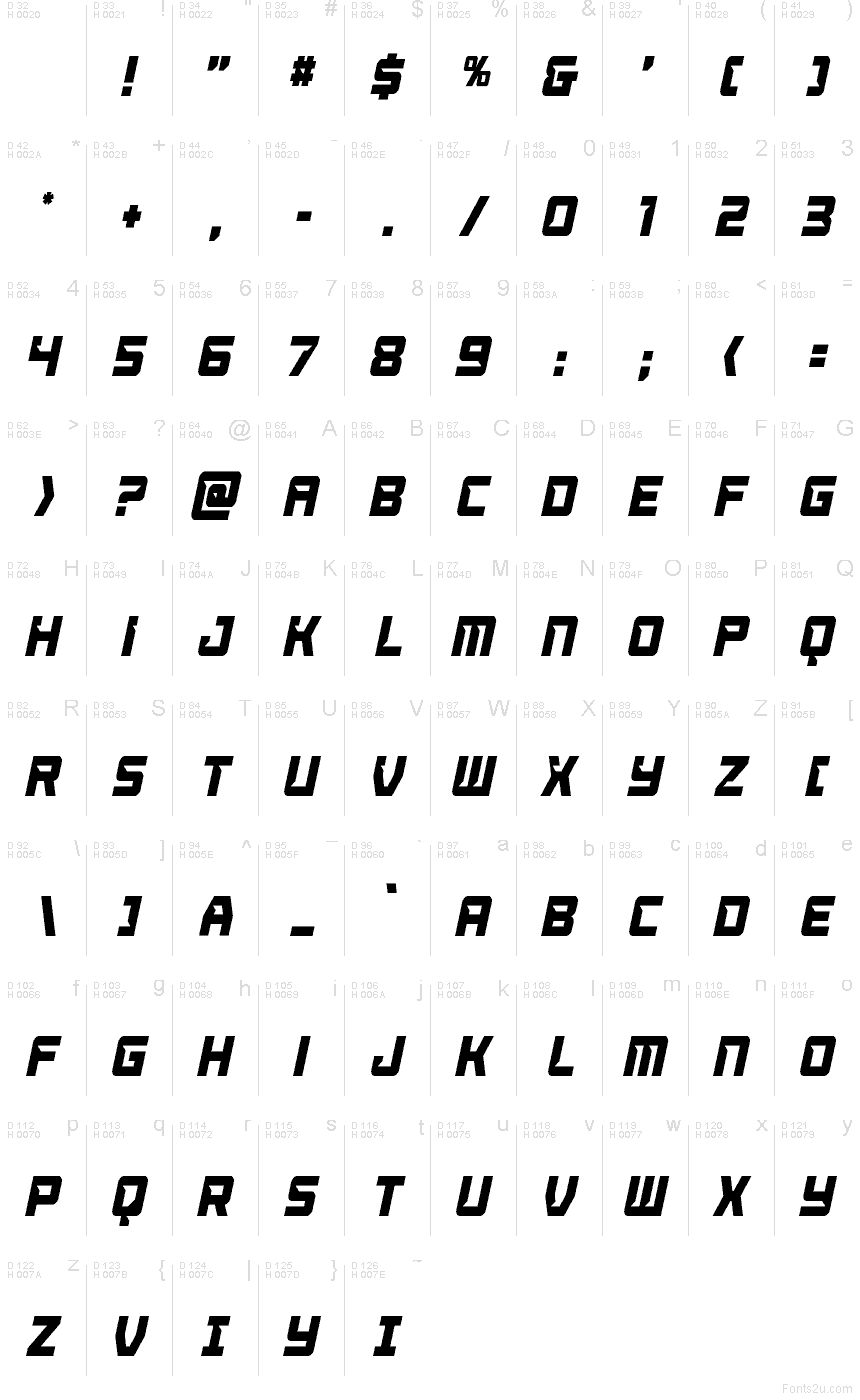
United Colony Condensed Italic od Iconian Fonts je bezplatné futuristické titulkové písmo tvorené len veľkými písmenami so sci-fi nádychom. Písmená pôsobia, akoby boli vyrezané z rýchlo sa pohybujúcich panelov – s úzkymi proporciami, strmými uhlami a blokovými spojmi, ktoré dodávajú celému dizajnu stlačený, vpred smerujúci rytmus.
Prirodzene zapadne do herných log, technologických plagátov, brandingov pre streamerov, filmových titulkov či na obálky, kde bezplatné písmo potrebuje skôr dynamiku než jemnosť. Keďže veľké písmená do seba zapadajú v tesných, hranatých tvaroch, skvele funguje aj v krátkych nadpisoch, tímových menách a monogramoch, ktoré si vyžadujú ostrý, mechanický vzhľad.